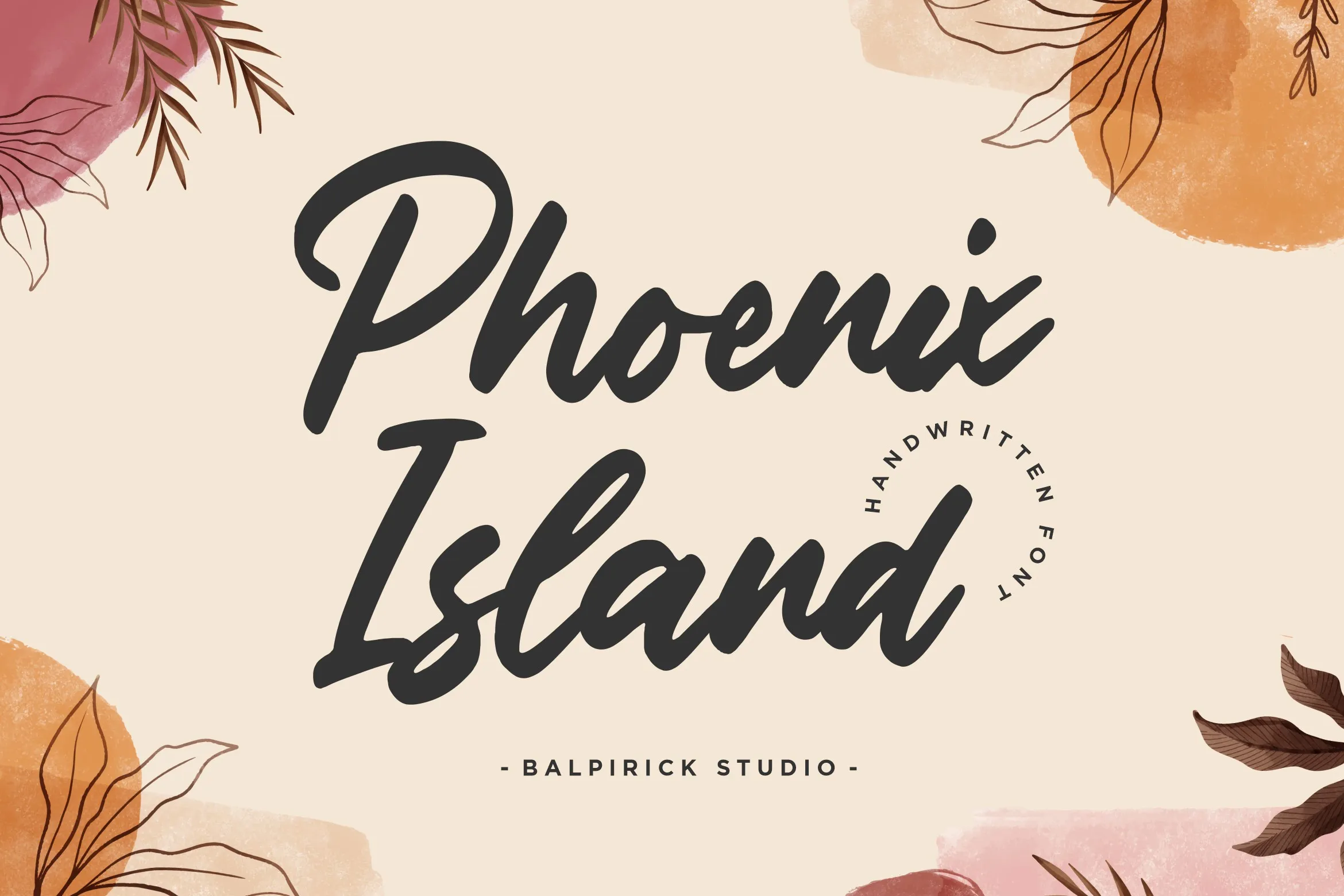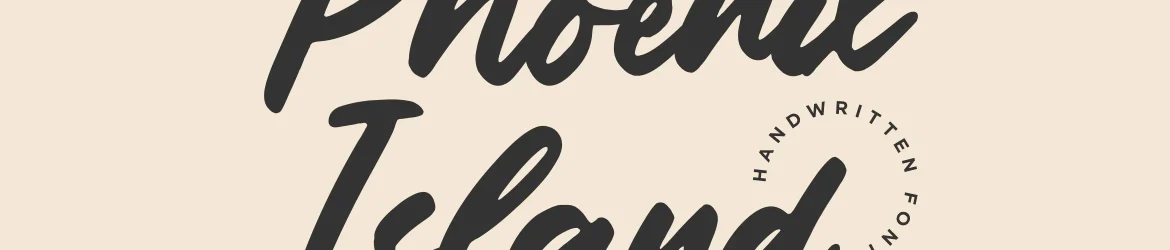
A Phoenix Island Font é uma elegante e eterna letra manuscrita perfeita para designers de rótulos criativos, logotipos e frases inspiradoras. Com cada letra carregando um toque único e belo, ela ajuda a dar vida aos seus projetos design. Este é um recurso vital para todos os que buscam uma fonte ideal para adicionar um toque de personalidade em suas criações visuais. A escolha da Phoenix Island Font irá certamente destacar seu trabalho ao criar designs memoráveis e irresistíveis. Seria o ideal para qualquer designer em busca de dar um toque especial à sua próxima obra.